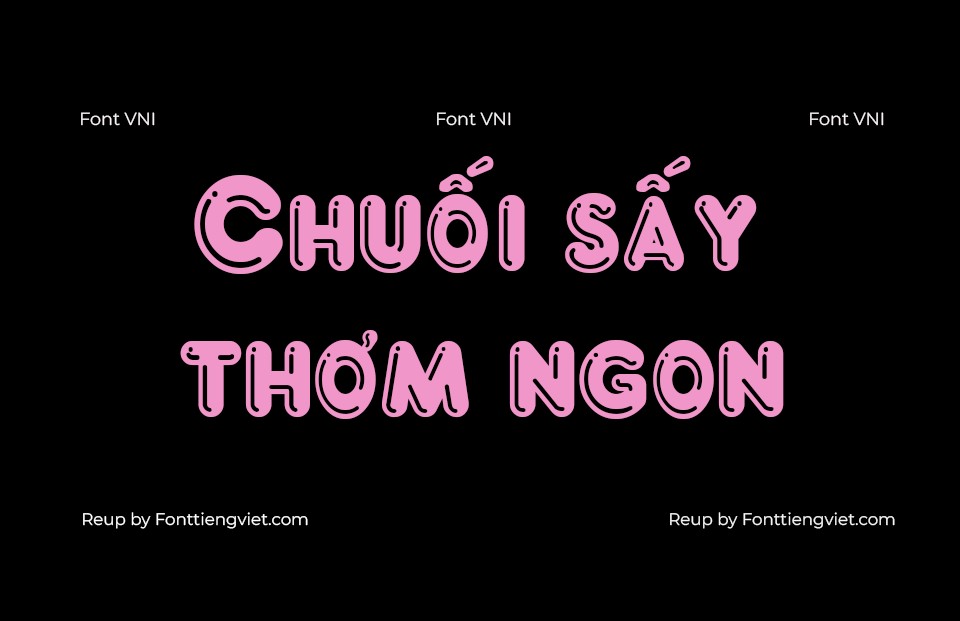
Giới thiệu về Font Việt hoá VNI Fato trong thiết kế đồ họa
Trong thế giới sáng tạo, việc lựa chọn một Font Miễn Phí phù hợp đóng vai trò quyết định đến thẩm mỹ của tác phẩm. Font Việt hoá VNI Fato là một trong những bộ phông chữ độc đáo, mang phong cách hiện đại xen lẫn nét cổ điển tinh tế. Với đường nét dày dặn và mạnh mẽ, bộ chữ này rất được ưa chuộng trong các dự án đòi hỏi sự nổi bật và cá tính cao. Đặc biệt, phiên bản này đã được tối ưu hóa hoàn toàn cho bảng mã VNI, giúp người dùng tại Việt Nam dễ dàng gõ tiếng Việt mà không lo lỗi hiển thị hay mất ký tự.
Ưu điểm nổi bật của bộ Font Việt hoá VNI Fato
Tính ứng dụng linh hoạt trong nhiều lĩnh vực
Font Việt hoá VNI Fato sở hữu cấu trúc ký tự rõ ràng, dễ đọc, phù hợp cho cả in ấn lẫn trình chiếu kỹ thuật số. Bạn có thể sử dụng bộ font này để thiết kế tiêu đề sách, banner quảng cáo, hoặc các ấn phẩm truyền thông học đường. Nhờ phong cách trình bày chuyên nghiệp, nó giúp thông điệp truyền tải trở nên ấn tượng và thu hút sự chú ý của người xem ngay từ cái nhìn đầu tiên.